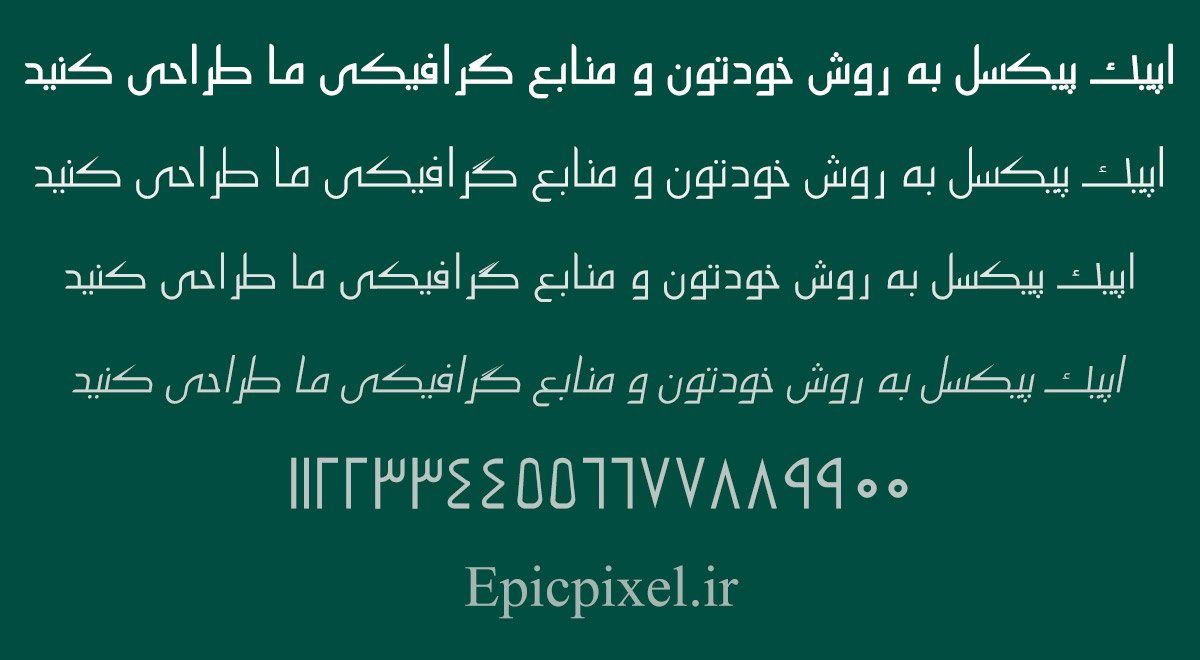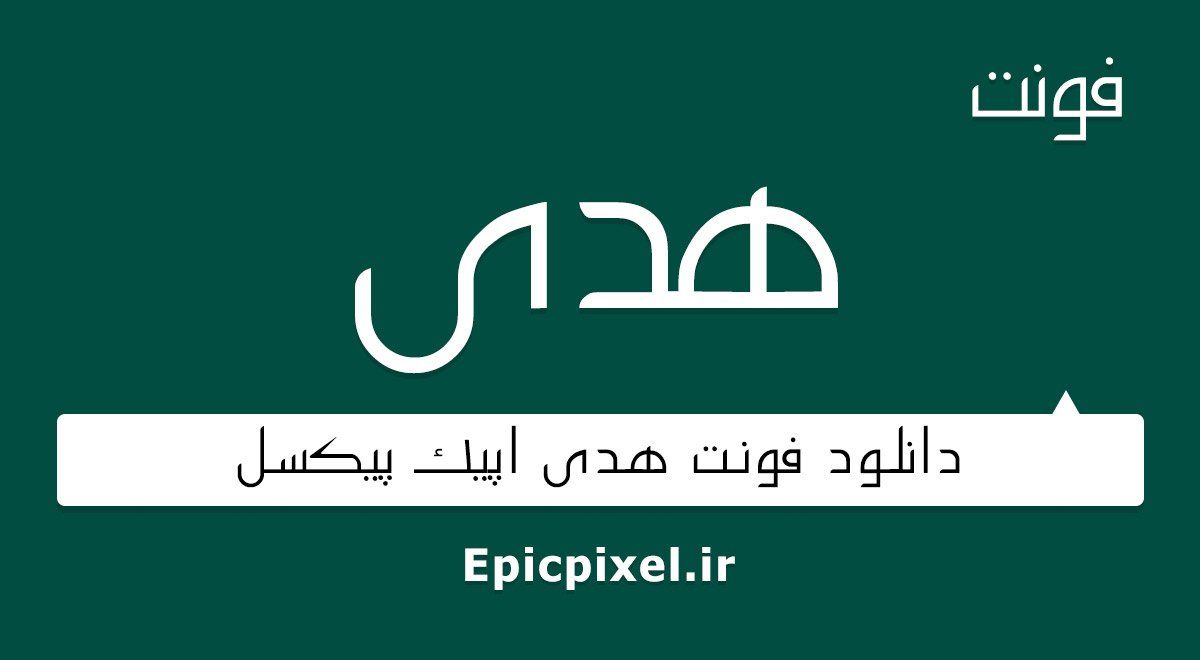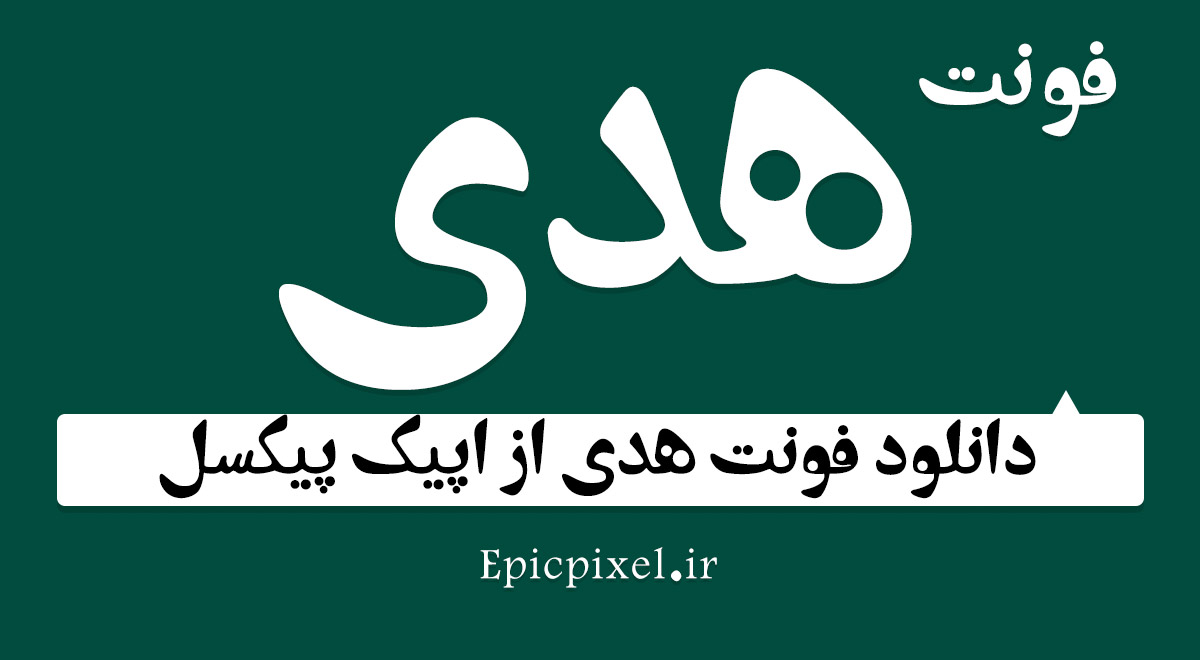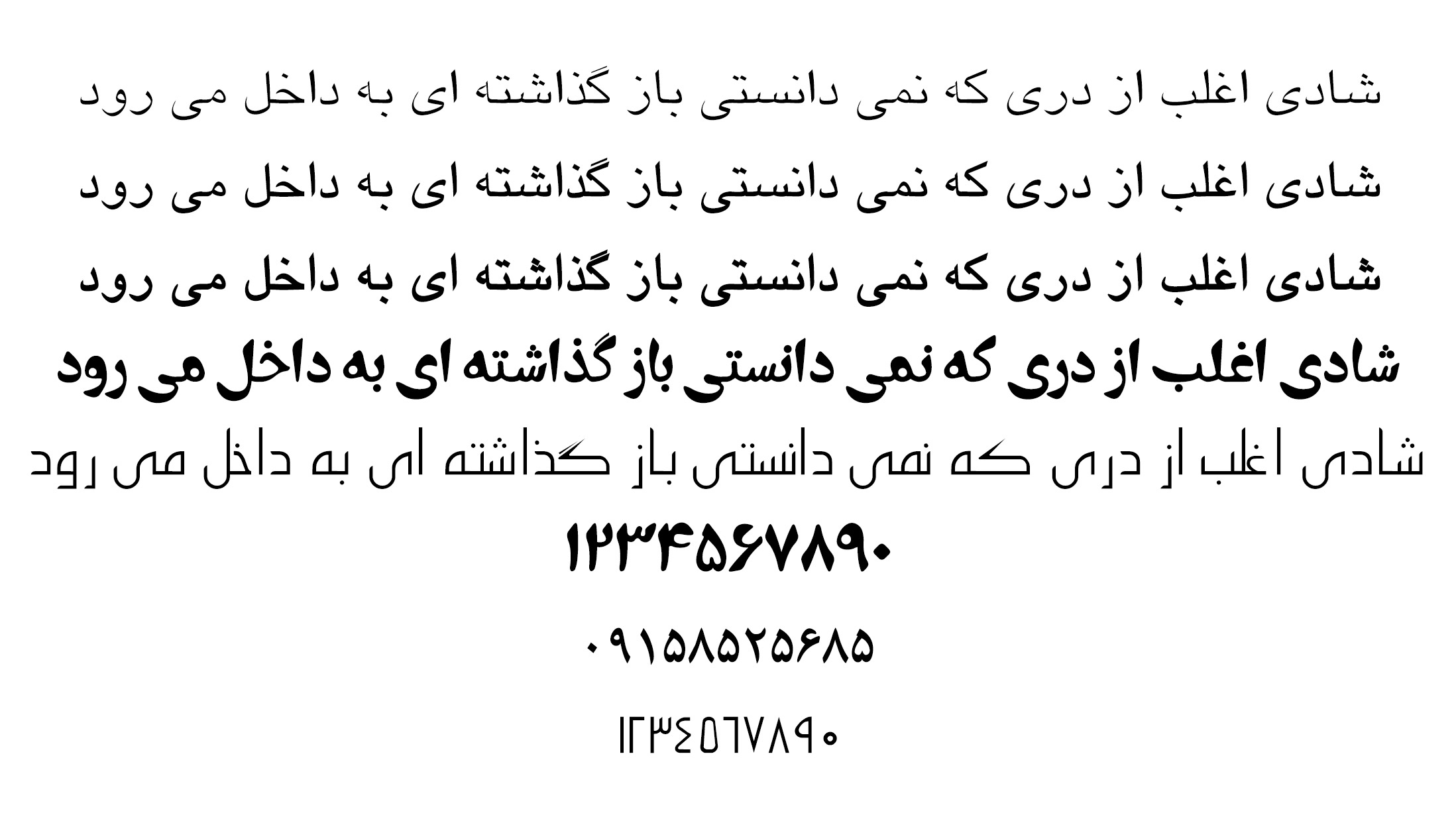
6 فونت هدی فارسی
فونت هدی چگونه فونت فانتزی با الهام از فونت نسخ ایرانی طراحی شد؟
تعریف فونت هدی و اهداف طراح آن
فونت هدی یک فونت فانتزی است که توسط هدی ترابیخواه، کارشناس ارشد گرافیک و مدرس دانشگاه، طراحی شده است. این فونت با ایجاد تغییرات جسورانه در فونتهای نسخ ایرانی مانند تیتر و زر بولد ایجاد شده است. تغییرات آنقدر زیاد و اغراق آمیز است که دیگر شما اثری از فونتهای زر بولد و تیتر را نمیبینید اما به هر صورت حالتی از آن را تشخیص میدهید. هدف طراح این فونت این بوده است که یک فونت جدید و متفاوت را برای طراحان گرافیک و علاقهمندان به تایپوگرافی فارسی ارائه دهد که در حین فانتزی بودن همچنان حالتی از جدیت و رسم بودن را نیز در خود داشته باشد. در این مقاله، ما به بررسی تاریخچه، ویژگیها، کاربردها و نحوه دانلود و نصب فونت هدی خواهیم پرداخت.
تاریخچه فونت نسخ و ویژگیهای آن
فونت نسخ یک نوع خط عربی است که در قرون وسطای اسلام به عنوان خط رسمی برای نگارش قرآن، حدیث، علم و ادب به کار میرفت. این خط با استفاده از قلم بامبو یا قلمپاره نوشته میشده است. ويژگيهای خط نسخ عبارتاند از: دارا بودن حالات مختلف بستگي به مكان حروف در كلمات، دارا بودن حروفي كه به صورت پياده يا پياده شده در كلمات قابل تشخيص هستند، دارا بودن حروفي كه به صورت ساده يا پيچيده در كلمات قابل تشخيص هستند، دارا بودن حروفي كه به صورت مستقيم يا منحني در كلمات قابل تشخيص هستند، دارا بودن حروفي كه به صورت ساده يا پيچيده در كلمات قابل تشخيص هستند. خط نسخ با سادگي، رواني و خوانائي خود به عنوان يكي از محبوبترين خطوط عربي شناخته شده است.
دانلودتغییرات جسورانه در فونت هدی و تأثیر آن بر ظاهر و خوانایی
فونت هدی با استفاده از فونتهای نسخ ایرانی مانند تیتر و زر بولد به عنوان پایه و اساس خود، تغییرات بسیار زیاد و جذابی را در حروف و کلمات ایجاد کرده است. برخی از این تغییرات عبارتاند از: بزرگ کردن یا کوچک کردن حروف به صورت نامتناسب، اضافه کردن یا حذف کردن نقطهها، خطوط و حلقهها، تغییر شکل یا جهت حروف، ایجاد فاصلههای بزرگ یا کوچک بین حروف، ادغام یا جداسازی حروف، اعمال رنگها و بافتهای مختلف. این تغییرات باعث شده است که فونت هدی یک ظاهر فانتزی و منحصر به فرد پیدا کند که در عین حال به خوبی با فرهنگ و زبان فارسی سازگار است. همچنین، این تغییرات تأثیر چندانی بر خوانایی فونت نداشتهاند و حتی در برخی موارد باعث جذابتر شدن محتوا شدهاند. برای مثال، در بعضی از حروف، نقطههای زائد حذف شدهاند که باعث سادگی و زیبایی بیشتر شدهاند. یا در بعضی از کلمات، حروف به صورت منحنی چیده شدهاند که باعث روانتر شدن خوانش شدهاند.
کاربردهای فونت هدی در طراحی گرافیک و تایپوگرافی
فونت هدی یک فونت مناسب برای طراحان گرافیک و علاقهمندان به تایپوگرافی فارسی است. این فونت میتواند در طرحهای مختلف مانند لوگو، پوستر، بروشور، کارت ویزیت، سربرگ، بنر، استیکر، تابلو، پوشش کتاب و مجله، سایت و اپلیکیشن و … به کار رود. فونت هدی با داشتن ظاهر فانتزی و جذاب، محتوای طرح را متمایز و جالب میکند. همچنین، با داشتن حالت جدی و رسم بودن، محتوای طرح را معتبر و قابل اعتماد میکند. فونت هدی با قابلیت تطبیق با رنگها و بافتهای مختلف، به طراح اجازه میدهد که خلاقانه با آن بازی کند و طرحهای متنوع و زیبا ایجاد کند.
خلاصهای از نکات کلیدی مقاله و دعوت به استفاده از فونت هدی
در این مقاله، ما با فونت هدی و ویژگیها، کاربردها و نحوه دانلود و نصب آن آشنا شدیم. فونت هدی یک فونت فانتزی است که با الهام از فونتهای نسخ ایرانی طراحی شده است. این فونت با ایجاد تغییرات جسورانه در حروف و کلمات، یک ظاهر جذاب و منحصر به فرد پیدا کرده است. همچنین، این فونت با حفظ جدیت و رسم بودن، یک خط مناسب برای طراحان گرافیک و علاقهمندان به تایپوگرافی است. این فونت به صورت رایگان قابل دانلود و نصب بر روی سیستم عاملهای مختلف است. ما پیشنهاد میکنیم که شما هم از این فونت زیبا در طرحهای خود استفاده کنید و لذت ببرید.
سؤالات متداول درباره فونت هدی
فونت هدی از چه فونتهایی الهام گرفته است؟
فونت هدی از فونتهای نسخ ایرانی مانند تیتر و زر بولد الهام گرفته است.
فونت هدی چه تغییراتی را در حروف و کلمات ایجاد کرده است؟
فونت هدی با بزرگ کردن یا کوچک کردن حروف به صورت نامتناسب، اضافه کردن یا حذف کردن نقطهها، خطوط و حلقهها، تغییر شکل یا جهت حروف، ایجاد فاصلههای بزرگ یا کوچک بین حروف، ادغام یا جداسازی حروف، اعمال رنگها و بافتهای مختلف، تغییرات جسورانهای را در حروف و کلمات ایجاد کرده است.
فونت هدی در چه طرحهایی قابل استفاده است؟
فونت هدی در طرحهای مختلف مانند لوگو، پوستر، بروشور، کارت ویزیت، سربرگ، بنر، استیکر، تابلو، پوشش کتاب و مجله، سایت و اپلیکیشن و … قابل استفاده است.